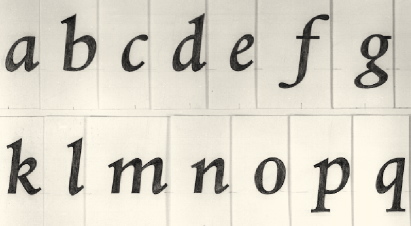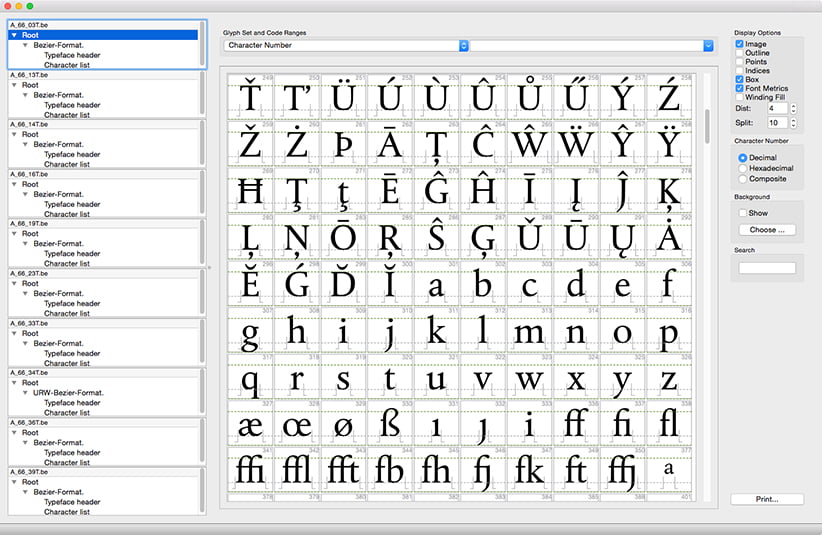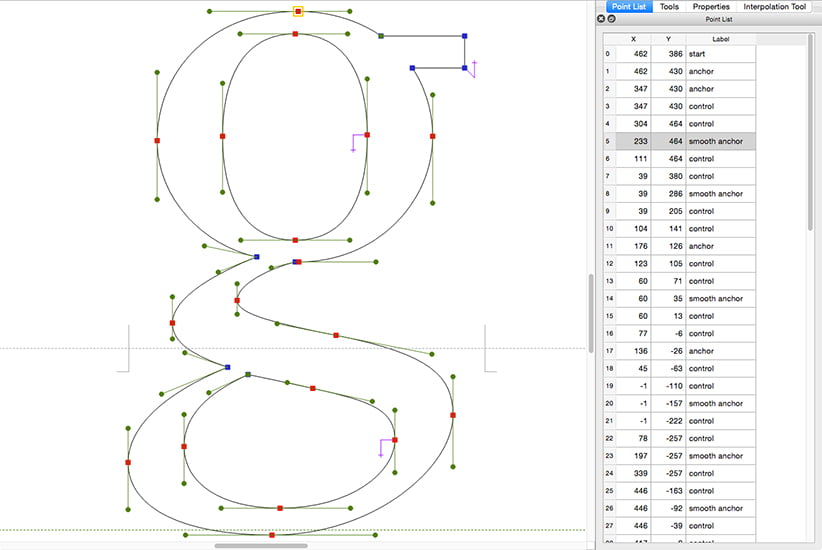
‘Een knappe kalligraaf’ schreef John Dreyfus over Chris Brand in het voorwoord van Letterontwerpers (Haarlem, 1987). De kalligrafie speelde een belangrijke rol in de ontstaansgeschiedenis van dtl Albertina en is terug te vinden in de details van het lettertype. Albertina was oorspronkelijk eind jaren vijftig van de twintigste eeuw door The Monotype Corporation Ltd. in productie genomen voor de ‘hete’ zetselgietmachine maar kwam door de tussentijdse ontwikkelingen van de technologie voor de Monophoto belichter op de markt. Het lettertype werd vernoemd naar de Koninklijke Bibliotheek te Brussel, waarvan de naam voluit Koninklijke Bibliotheek Albert 1 luidt. De eerste toepassing was in de catalogus bij de tentoonstelling Stanley Morison en de typografische traditie in de Koninklijke Bibliotheek in 1966. Stanley Morison selecteerde persoonlijk Albertina voor dit doel. Voor de digitale bewerking door de Dutch Type Library van Albertina werden de werktekeningen van Monotype met de oorspronkelijke tekeningen van Chris Brand vergeleken. Er werd besloten om nieuwe contouren te maken op basis van de oorspronkelijke ontwerptekeningen. De door Chris Brand getekende verfijningen konden op deze manier in de digitale versie worden gehandhaafd. Daarbij kwam het feit, dat de voor de Monophoto uitgebrachte versie had geleden onder de beperkingen van het eenheden-systeem van de Monotype. Er was geen reden om deze beperkingen over te nemen in de digitale versie. Met volledige steun van zowel Chris Brand als van Monotype Typography ontstond zo een nieuwe optekening van Albertina. De digitale versie heeft het elegante contrast en gewicht van de oorspronkelijke tekeningen. | ||||||||||||||||